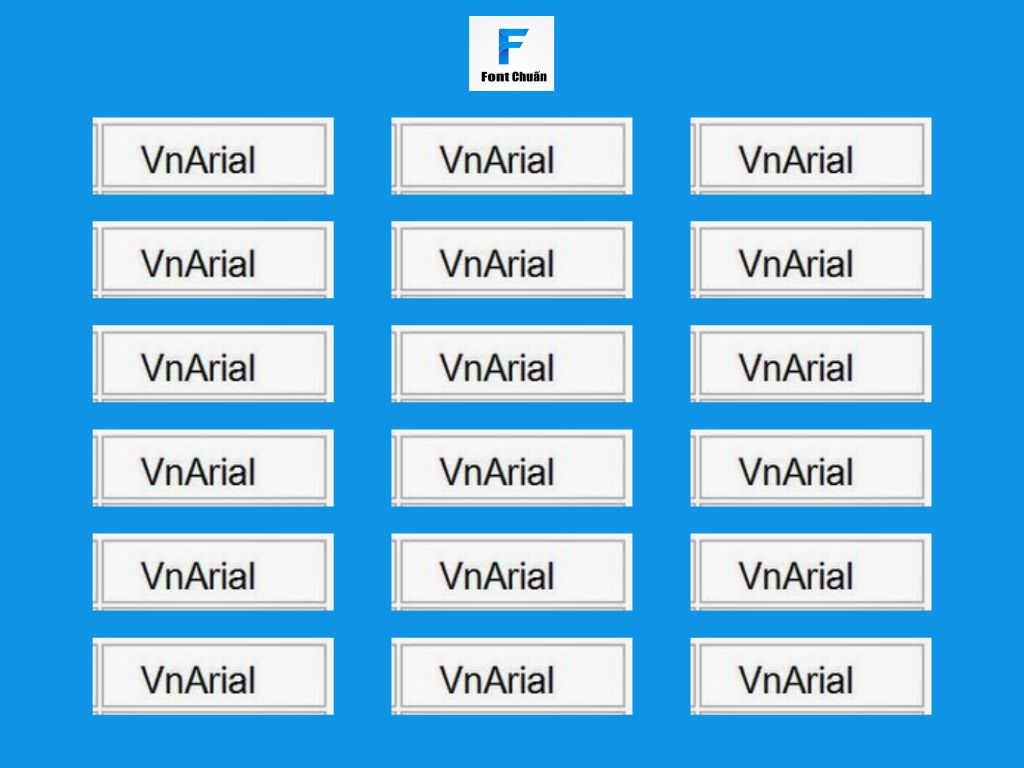
Giới thiệu font chữ VnTime
Font VnTime là gì, đặc điểm nhận diện
VnTime là bộ font Việt hóa thuộc bảng mã TCVN3, từng được dùng phổ biến trong soạn thảo văn bản ở Việt Nam những năm trước khi Unicode ra đời. Font có kiểu chữ Serif truyền thống, dễ đọc, thường thấy trong tài liệu hành chính, giáo dục và các mẫu biểu.
Vì sao VnTime vẫn còn phổ biến trong soạn thảo văn bản cũ
Mặc dù Unicode đã trở thành chuẩn hiện nay, VnTime vẫn được sử dụng rộng rãi vì:
- Nhiều văn bản cũ được soạn bằng VnTime, nếu không cài sẽ bị lỗi hiển thị.
- Một số cơ quan, trường học vẫn lưu trữ dữ liệu theo chuẩn TCVN3.
- Người dùng lâu năm đã quen gõ bằng font này nên vẫn duy trì.
Dù đã quen thuộc với font chữ VnTime trong nhiều năm, không phải ai cũng để ý đến cách nó được trình bày trên trang. Chính việc kiểm soát cỡ chữ, dòng và khoảng trắng đã nâng VnTime từ một font văn bản đơn thuần thành yếu tố của Typography trong thiết kế đồ họa.
Bộ sưu tập 300+ Font chữ VnTime thông dụng
Khi nhắc đến font VnTime, không chỉ có một kiểu duy nhất mà còn có nhiều biến thể khác nhau để đáp ứng nhu cầu soạn thảo đa dạng. Dưới đây là 4 font VnTime thông dụng nhất mà bạn thường gặp trong văn bản:
VnTime thường
Đây là kiểu chữ mặc định, nét chữ mảnh, cân đối và dễ đọc. Thường được sử dụng cho nội dung chính của văn bản, tài liệu hành chính, hoặc các đoạn chữ dài.
VnTimeH
Phiên bản này có ký tự rộng và thoáng hơn so với font chữ VnTime thường. Phù hợp khi muốn trình bày tài liệu rõ ràng, dễ nhìn hoặc khi in ấn cần chữ không bị dày đặc.
Font Vn Black
Kiểu chữ đậm, rõ ràng, phù hợp cho tiêu đề và nhấn mạnh nội dung quan trọng trong tài liệu.
Font VnArial
Phông chữ đơn giản, dễ đọc, thích hợp sử dụng trong văn bản dài, bài giảng và tài liệu học tập.
Font chữ VnTime tương đối dễ dùng, phù hợp cho người mới làm quen với soạn thảo văn bản. Tuy nhiên, để trình bày đúng chuẩn, bạn cần nắm rõ cách Việt Hóa font chữ trong từng trường hợp cụ thể.